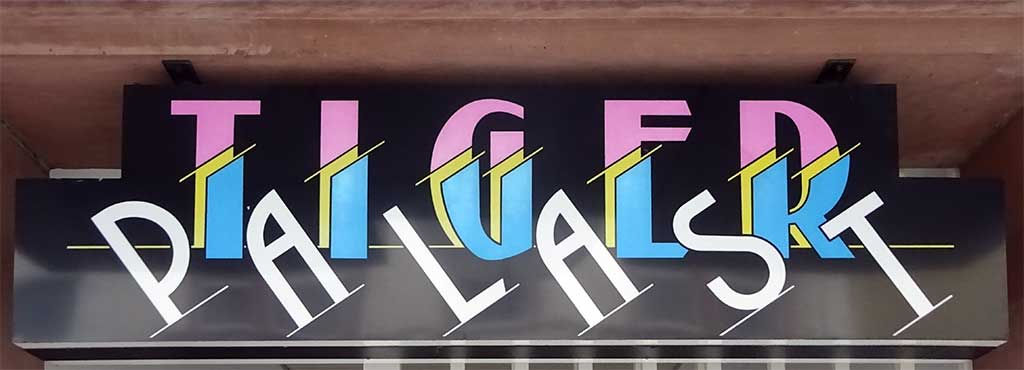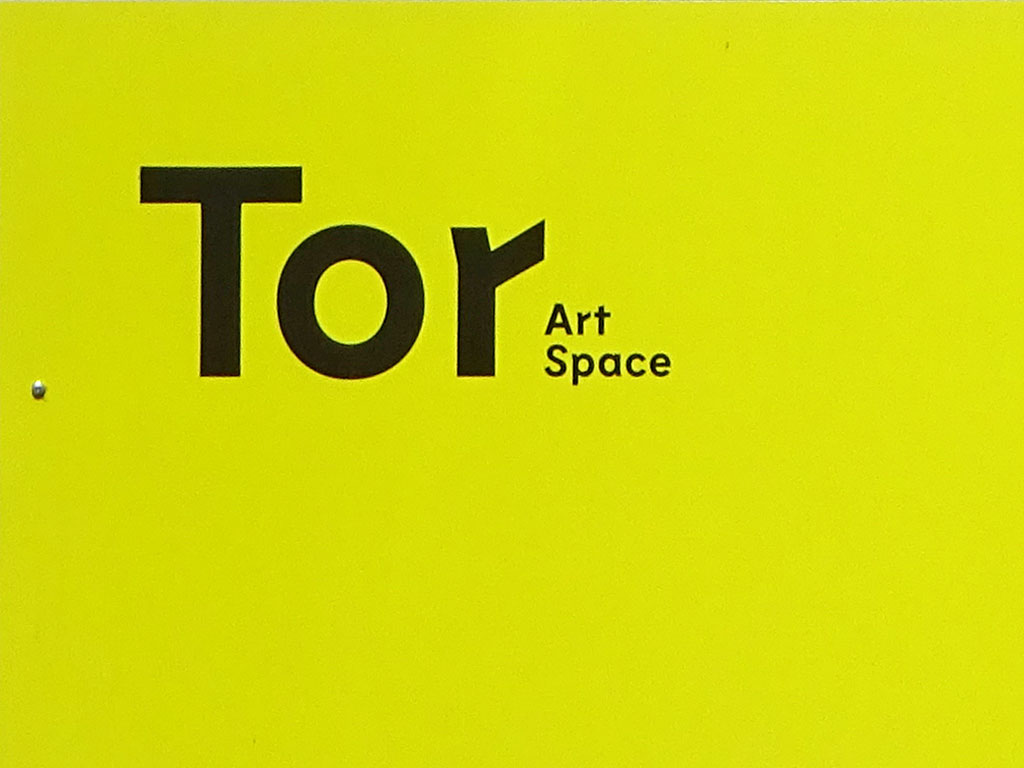
Typografie in Frankfurt - Jazz Haus
Typografie, Schilder & Logos in Frankfurt (8)
Durchweg klein oder groß geschriebene Wörter, mehrfarbige Buchstaben oder auch unterschiedliche Schreibrichtungen sind nur einige der Stilmittel, die bei der Gestaltung von Schriftzügen für Gastronomiebetriebe und Kunst- und Kultureinrichtungen in Frankfurt am Main verwendet wurden. Der 8. Teil der Serie Typografie, Schilder & Logos in Frankfurt enthält 14 Fotos, von A wie Alte Liebe bis Z wie Zoom.
Typografie in Frankfurt - Zoom
Typografie in Frankfurt - Tor Art Space
Typografie in Frankfurt - Silbergold
Typografie in Frankfurt - HfMDK
Typografie in Frankfurt - Jazz Haus
Typografie in Frankfurt - Alte Liebe
Typografie in Frankfurt - Schirn Kunsthalle
Typografie in Frankfurt - Tumult
Typografie in Frankfurt - Wein Schirn
Typografie in Frankfurt - Tiger Palast
Typografie in Frankfurt - Cooky's
Typografie in Frankfurt - Central
Typografie in Frankfurt - Circus
Typografie in Frankfurt - Mona Lisa